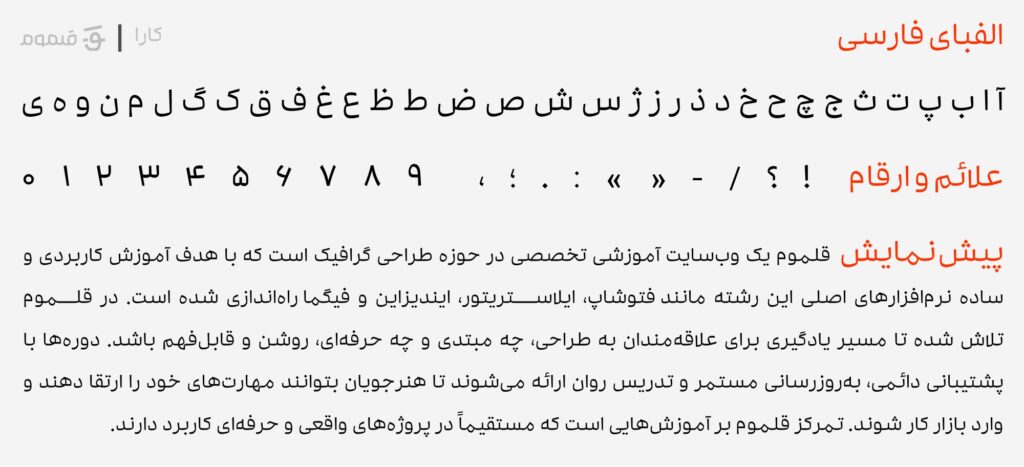
خانواده فونت کارا
فونت کارا یکی از فونتهای حرفهای و چشمنواز فارسی است که توسط دامون زنجانزاده طراحی شده. این تایپفیس در سه وزن مختلف ارائه شده و با طراحی مدرن و متعادل خود، گزینهای مناسب برای استفاده در تیترها، پوسترها، رابطهای کاربری و حتی متون کوتاه به شمار میرود.
ویژگی بارز کارا، ترکیب خلاقیت در فرم حروف با حفظ خوانایی بالاست؛ به همین دلیل میتواند در پروژههایی که به ظاهری متفاوت و متمایز نیاز دارند، بسیار کاربردی باشد. این فونت بهصورت رایگان در دسترس کاربران قرار گرفته و در فرمت استاندارد TTF عرضه میشود، بنابراین در انواع نرمافزارهای طراحی و محیطهای دیجیتال بهراحتی قابل استفاده است.